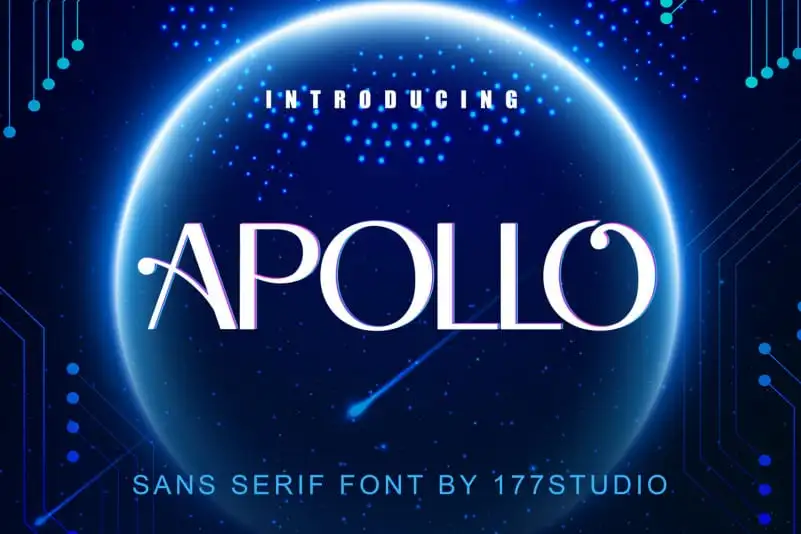
Apollo Sans Serif Font – Free Demo – Download Grátis
A Apollo Sans Serif Font é uma nova opção para designers que buscam tanto elegância quanto modernidade em seu próximo projeto visual. Esta fonte sem serif oferece linhas contrastantes e formas bem equilibradas, criando um estilo único que destaca-se na composição de design. Suas linhas fortes e sua forma equilibrada garantem uma legibilidade ótima, perfeita tanto para textos quanto para logomarcas ou títulos de capa. Seu uso no estilo regular da fonte é ideal para qualquer tipo de texto, enquanto as versões mais pesadas são perfeitamente adequadas para criar destaque nos elementos visuais-chave do design, como logos e cabeçalhos. A Apollo Sans Serif Font é uma escolha inteligente para quem busca uma fonte moderna que se destacará em seu projeto visual. Ela é uma ótima alternativa para aqueles buscando algo diferente daquela serif clássica ou das fonts geométricas convencionais, mas mantendo a elegância de um tipo sans serif.